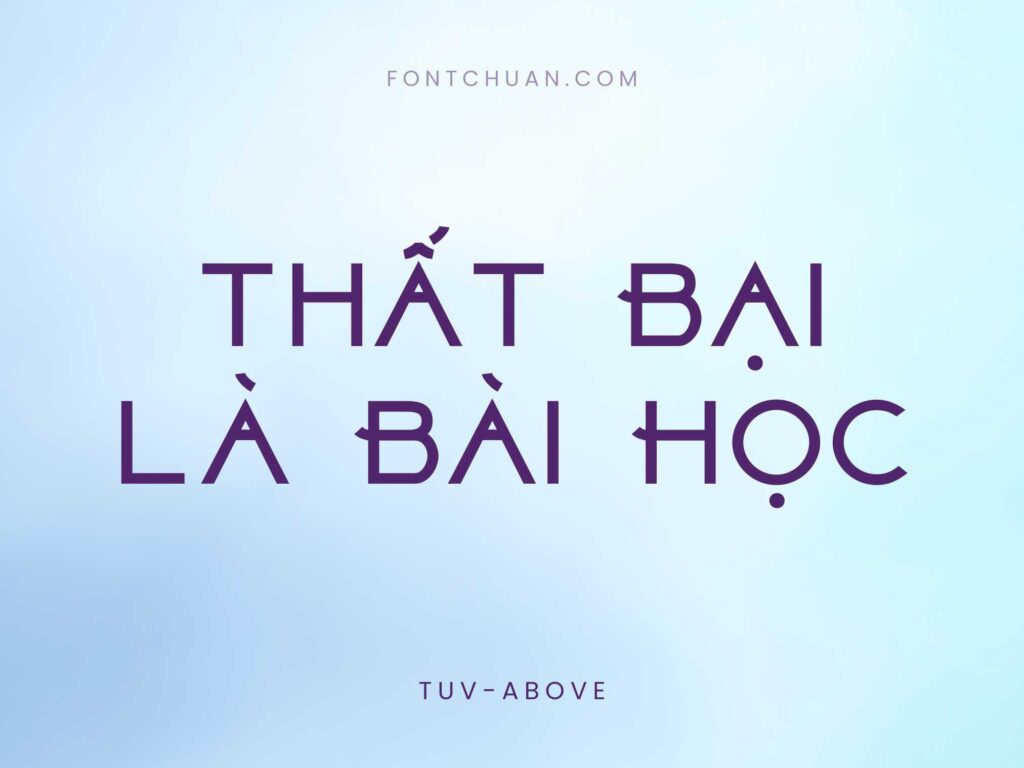
Font TUV Above Trọn Bộ Việt Hóa
TUV Above là một bộ Font Sans serif được thiết kế với tất cả các ký tự in hoa, bao gồm 4 kiểu: Light, Regular, Bold và Black. Font này hoàn hảo để tạo ra các thiết kế sang trọng và tinh tế, phù hợp cho các dự án như bố cục tạp chí thời trang, thiết kế logo, thiệp mời hoặc trích dẫn. Với những đường nét rõ ràng và sức hấp dẫn vượt thời gian, TUV Above không chỉ là một lựa chọn cho các dự án thiết kế hiện đại mà còn có thể trở thành Font chữ quảng cáo lý tưởng, giúp nội dung truyền thông nổi bật và thu hút. Font đã được Việt hóa để hỗ trợ tiếng Việt bởi Thùy Uyên, giúp người dùng Việt Nam dễ dàng sử dụng trong các dự án sáng tạo. Font này được sưu tầm và chia
Đặc điểm thiết kế của TUV Above bao gồm các ký tự in hoa với sự khác biệt giữa chế độ thường và in hoa, tạo nên sự linh hoạt trong thiết kế. Font này phù hợp cho nhiều ứng dụng như thiết kế tiêu đề, logo, thiệp mời và các dự án sáng tạo khác. Đặc biệt, khi được áp dụng làm font chữ Trung Thu, TUV Above mang lại sự kết hợp độc đáo giữa vẻ hiện đại và nét truyền thống, rất thích hợp cho các poster lễ hội, banner quảng cáo hoặc các ấn phẩm truyền thông sự kiện. Các ngành nghề phù hợp bao gồm thời trang, quảng cáo và thiết kế đồ họa.